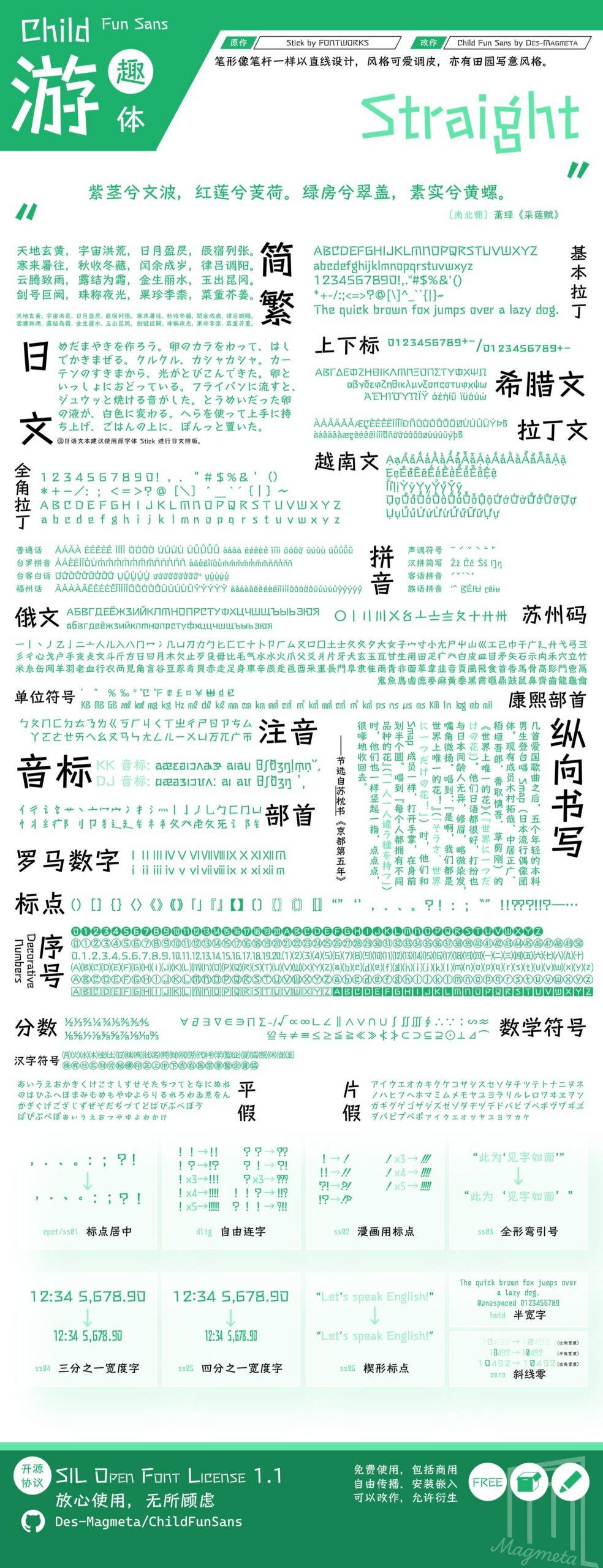
一款开源简体中文字体,基于 Fontworks(今 Monotype 株式会社)的 Stick 衍生。
游趣体因笔形像笔杆一样以直线设计,而被视为一款既可爱调皮,亦有田园写意风格的字体,本人基于 Fontworks 出品的日文字体 Stick 增补、调整字形,并编辑、适当增加 OpenType 特性,以满足简体中文的使用需求。
补字计划
简体部分
- 目标字汇①范围内修改 G 形②;
- 增补原字库中含有的繁体字对应的简化字;
- 现代汉语常用字表 3500 字;
- GB/T 2312-1980 汉字部分 6763 字;
- 通用规范汉字表 8105 字;
- 现代汉语通用字表 7000 字;
- 按需添加一些表外字,参照「霞鹜开源字体外字初步整理一览表」第一部分。
① 包括《义务教育语文课程常用字表》、GB/T 2312-1980、《现代汉语通用字表》《通用规范汉字表》。
② 部分字形差异视为设计特性,不做修改,如「厶」「幺」「亥」等字。
繁体部分
- GB/T 12345-1990(原文)6866 个汉字;
- 台湾地区「常用国字标准字体表」4808 个繁体常用汉字;
- BIG5 一级(常用)汉字 5401 个;
- 「JF 当务字集」基本包所含汉字;
- 香港地区「常用字字形表」 常用汉字及部分异体字;
- 《通用规范汉字表》附件「规范字与繁体字、异体字对照表」中的繁体字列(一、二、三级)。
后续版本将跟进繁体版更新,字形将与繁体版大致相同。
- 本人并不是专业的设计师,并未考虑设计美感,所以看起来可能略丑,补进去的字与原版可能略有违和感,且在新补字符中部分字的轮廓曲线会有毛刺。此外由于时间仓促,并没有多余的时间细修,部分字的部件拼接会很生硬。如有字形优化建议,请在 Issue #1 提出。如需请求添加目标范围以外的字符,请在 Issue #2 提出,不要另开议题,以便于整理。 (以上两个议题均已加上 long term 标签,且均已在 Issues 页面置顶。)
- 在补齐 GB/T 2312 前,此字体将出现一定的缺字可能。在不介意字体回退的情况下,如需支持缺字字符,请移步「游趣体融合」。 此项目 0.400 版本已补齐 GB/T 2312,「游趣体融合」已永久停更并归档处理。
- 自 0.300 版本起,「游趣体」支持 Unicode 变体序列(Unicode Variation Sequences, UVS),用于弯引号
“‘’”宽度和全角标点符号,.、。:;!?位置的选择,支持变体序列的字符和所搭配的选择符详见「游趣体」变体序列一览表。WPS Office、PowerPoint (Microsoft 365) 软件不支持此特性,使用时需留意。 - 部分软件(如 PowerPoint 365)中,使用该字体可能会出现竖排文本显示异常的问题(如弯引号不能正确显示)。关于此问题,详见 Issue #3。
- 自 0.310 版起,「游趣体」项目在同一版本中同时发布完整版和简体版,除收录汉字数量上的差异外,部分符号的字形存在一定差异。差异字符详见文件内容差异一览。
- 调整近 160 汉字字形;
- 新增部分汉字,补全 GB/T 12345-1990 字表。